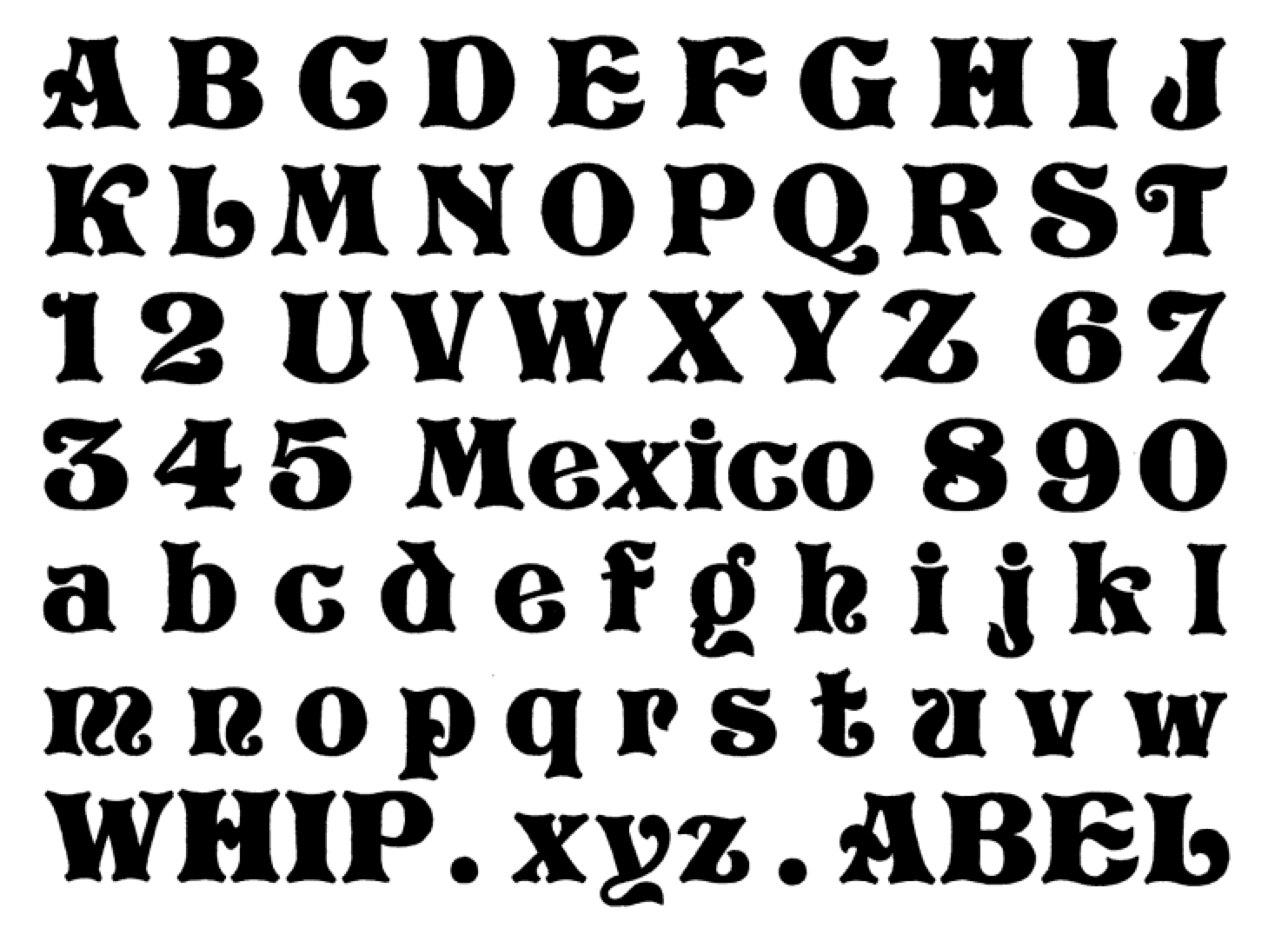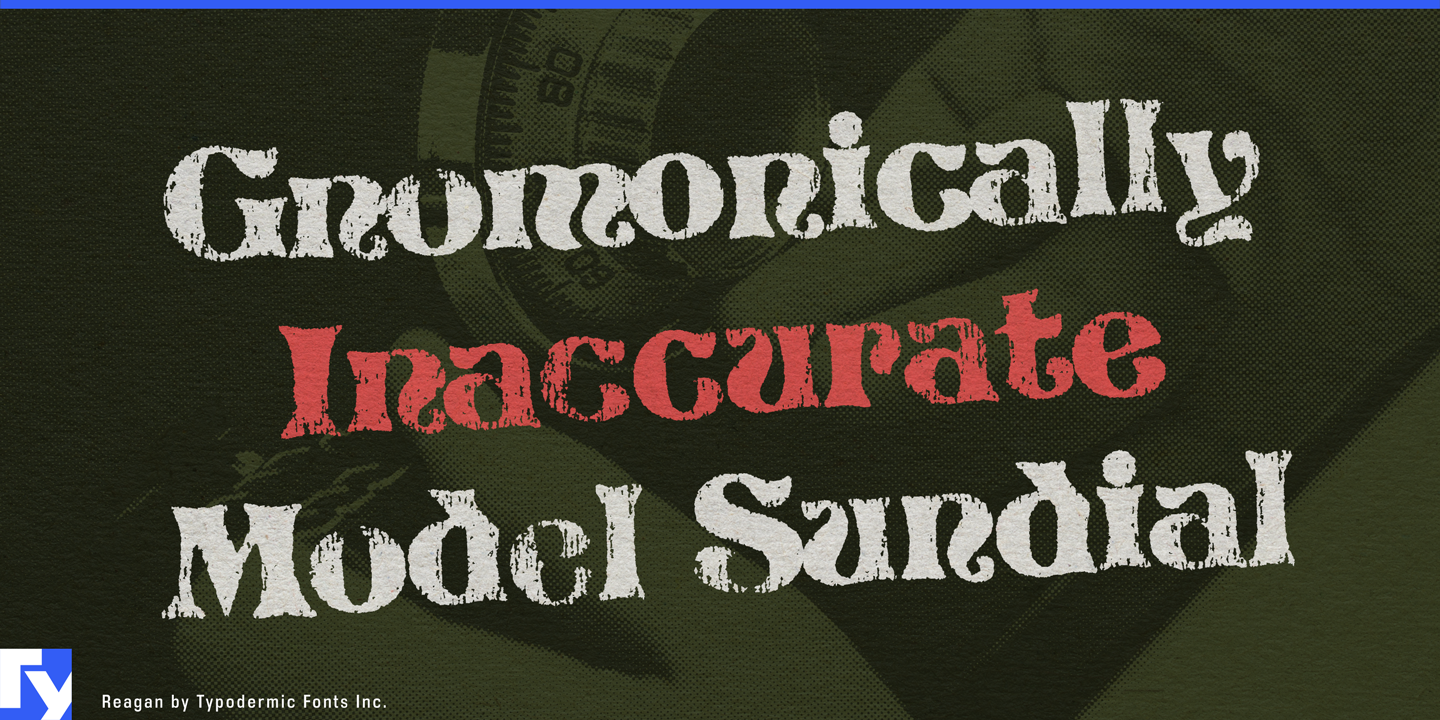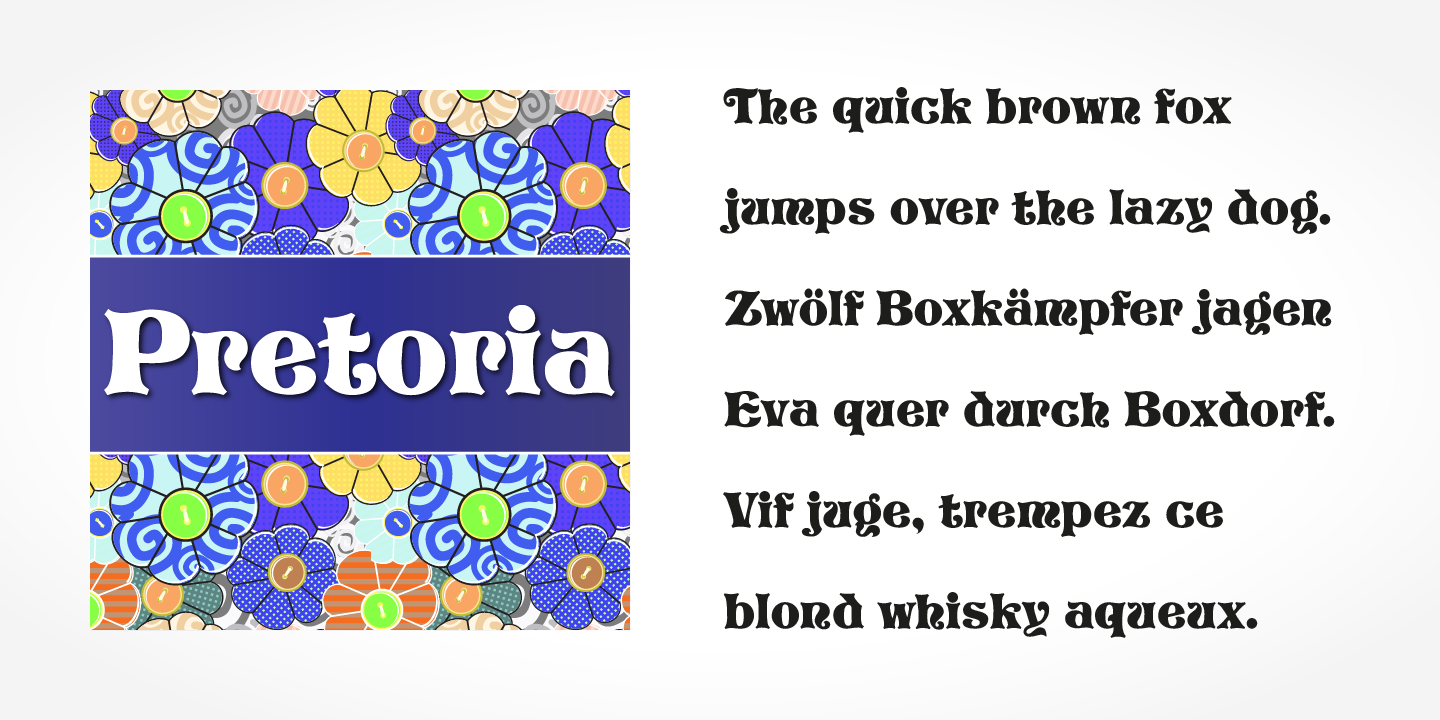
Font-Wiki: Pretorian
• Antiqua dekorativ
Die Jugendstilschrift Pretorian erschien um 1900 bei der englischer Foundry P. M. Shanks & Co als ein Hausschnitt ohne Angabe eines Schriftgestalters.
Es existieren verschiedene Digitalisierungen. Eine umfangreiche in vier Schnitten gibt es von DTP Types. Ray Larabies Reagan gibt das Design »verwittert« wieder.
Bleisatzversion
Softmaker-Digitalisierung
Reagan von Ray Larabie